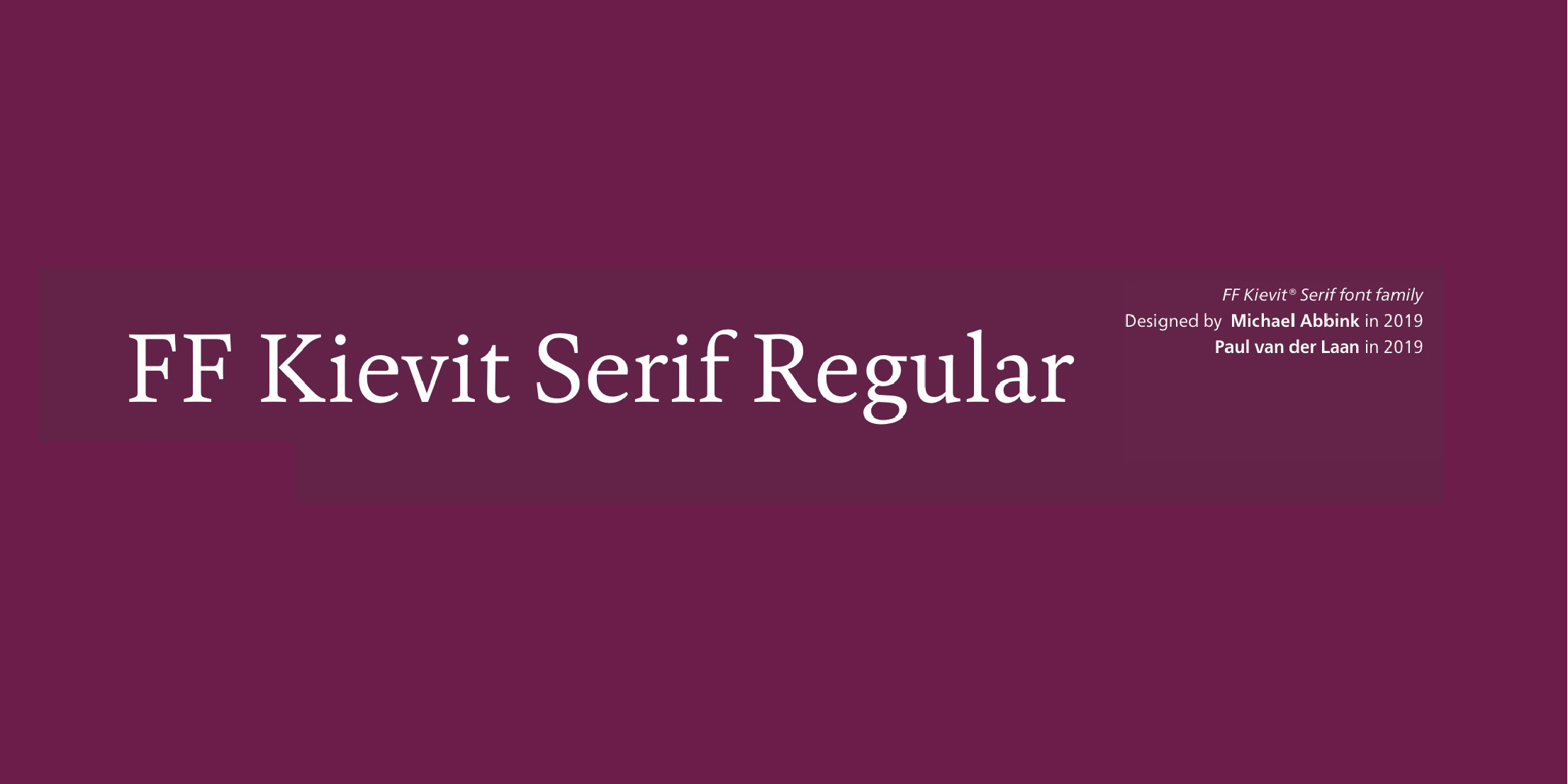
FF Kievit® Serif
FF Kievit® Serif,这款字体结构工整、笔画清晰,兼顾美观与易读性,适用于标题、正文、海报、包装、LOGO 等多种场景。字形优雅稳定,风格百搭耐看,适配日常排版与创意设计,让文字呈现更舒适、更具质感。FF Kievit® Serif一笔一画,皆是细节,以均衡的比例、流畅的线条打造舒适视觉体验,字形端正大气,风格简约现代。无论是商业设计、品牌宣传还是日常排版,都能轻松驾驭,让文字更有格调与力量。FF Kievit® Serif字体下载。
FF Kievit Serif巧妙地将旧式设计特点和21世纪的风采融合到一套简洁、直白的字体中,它帮助品牌能有效清晰地表达自己的声音,在印刷和数字环境中都可以很好的显示文本。FF Kievit的灵感来自Garamond和Granjon等经典设计, FF Kievit Serif由Michael Abbink、Paul van der Laan合作绘制,包括FF Kievtt和FF Kievot Slab。FF Kievit Serif作为一款多才多艺、清晰易读的设计字体而独树一帜。其宽大的字腔,较大的x高,确保FF Kievit Serif在纸媒和交互数字媒体环境中都能够很好地转换。常规体、文本体、粗体非常适合长文本,还提供连字、数字和小型大写字母。此外,FF Kievit Serif还支持多语言体系。